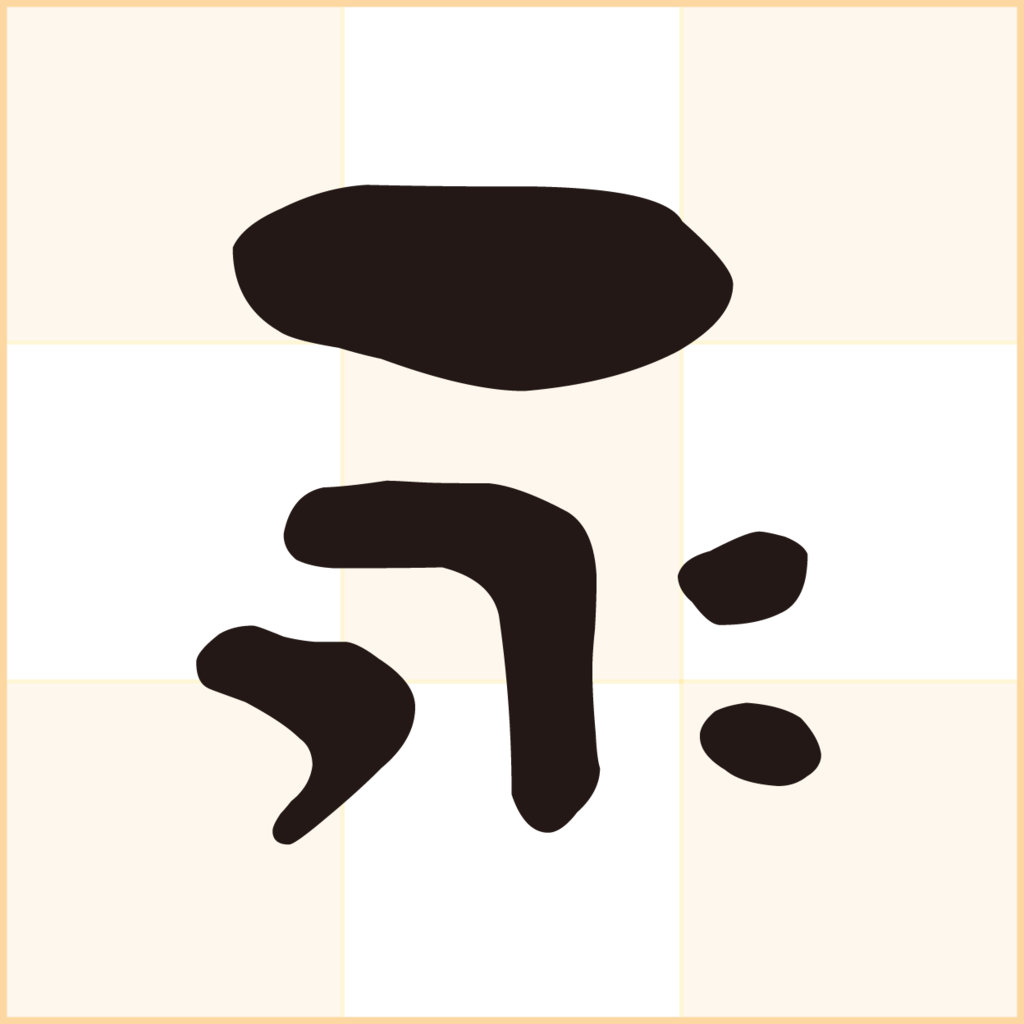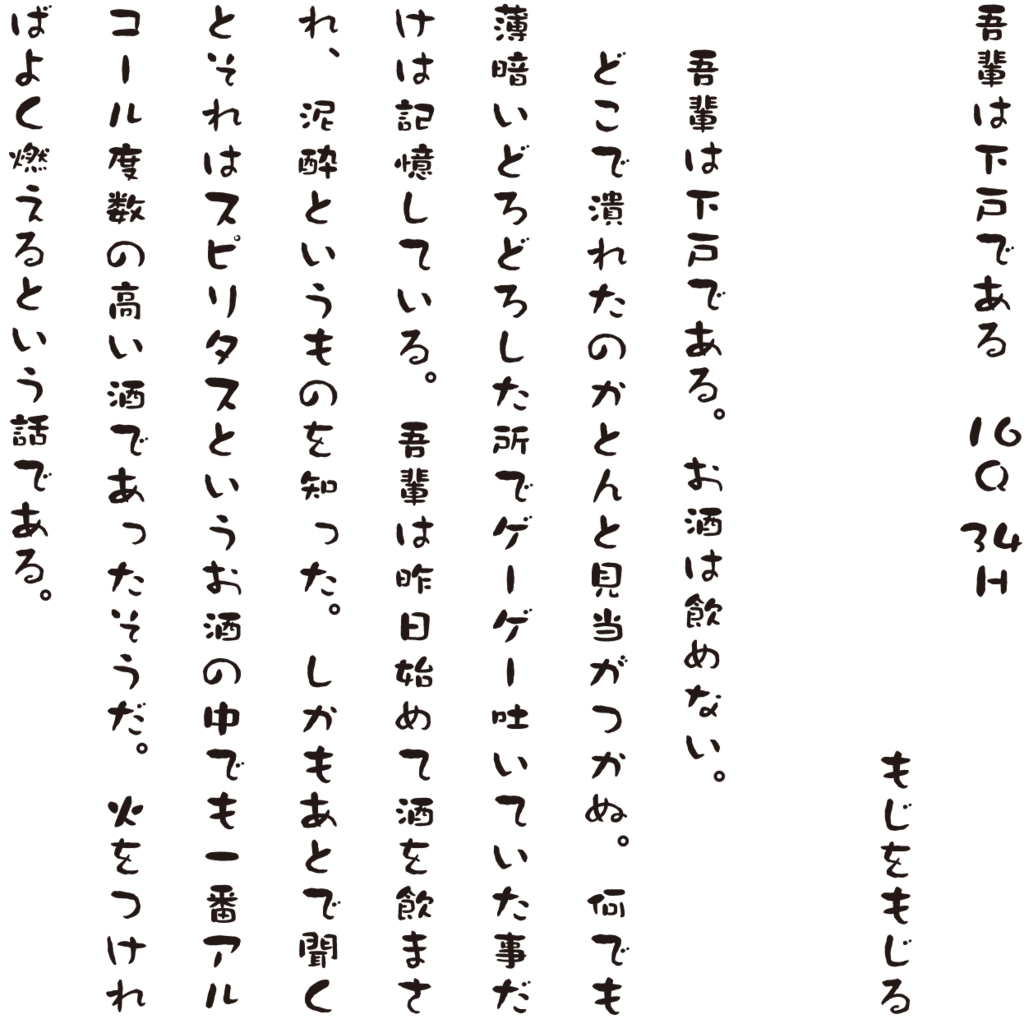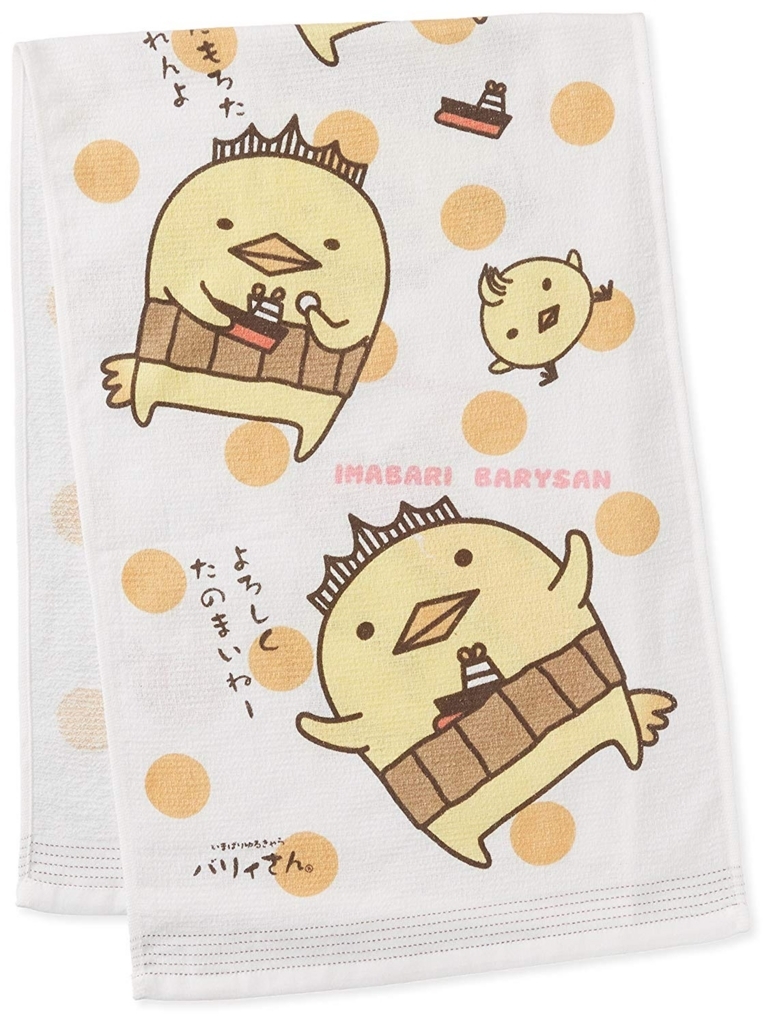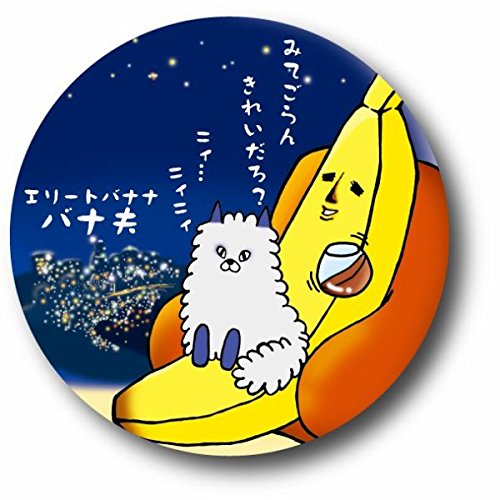
クラフト墨
なんだかほっこりさせる丸っこい墨文字のフォント。
ゆるキャラに使用される率も高い脱力系書体。
クラフト墨の組見本
新元号「令和」のクラフト墨書体見本
新元号「令和」のクラフト墨の書体見本。
街の看板までテレビ番組のテロップよく見かけるフォント・クラフト墨
どことなくゆる~い空気感をまとった書体デザインのため、街の看板から食べ物のパッケージ、「いまばり バリィさん」や「エリートバナナ バナ夫」などのゆるキャラのロゴ、テレビ番組のテロップまで幅広く見かけるフォントである。
クラフト墨使用事例:「ピクミン」シリーズ
任天堂の大人気ゲーム「ピクミン」シリーズのゲーム画面に使用されている独特な文字はダイナフォントの「クラフト墨」。
クラフト墨使用例「俺の株式会社」
クラフト墨使用例「和菓子のアン/アンと青春/アンと愛情」
クラフト墨使用例「塩の花シリーズ」
クラフト墨使用例「吉田類の酒場放浪記」
クラフト墨使用例「いまばり バリィさん」
クラフト墨使用例「エリートバナナ バナ夫」
▼クラフト墨は「エリートバナナ バナ夫」で使用されている。